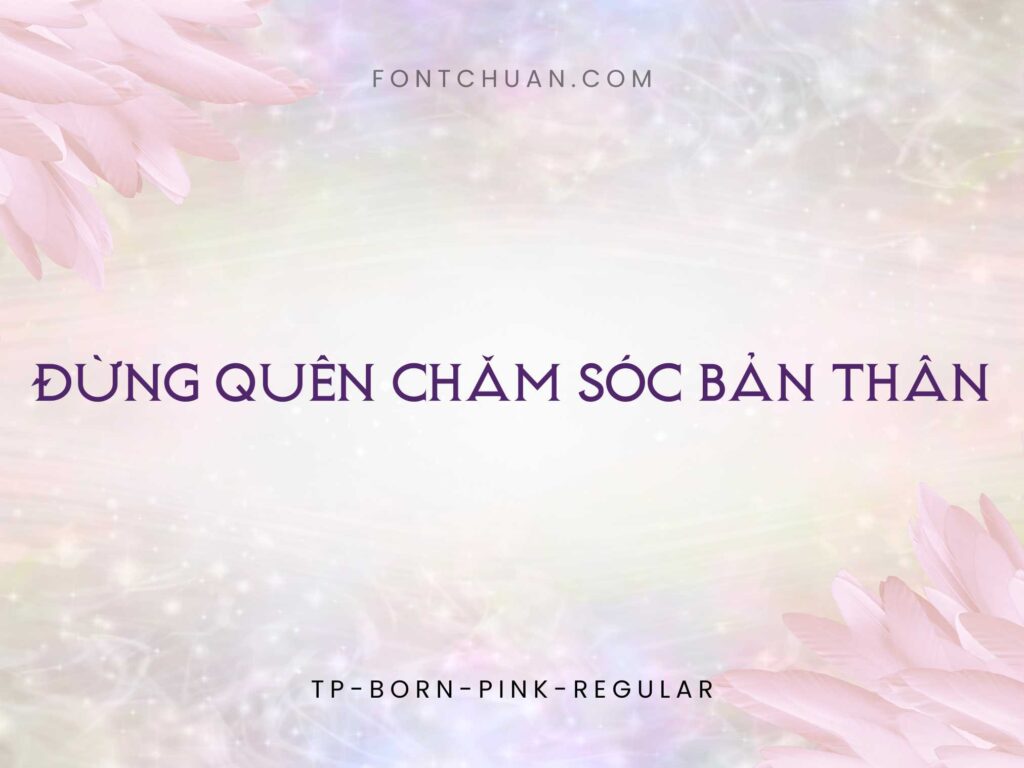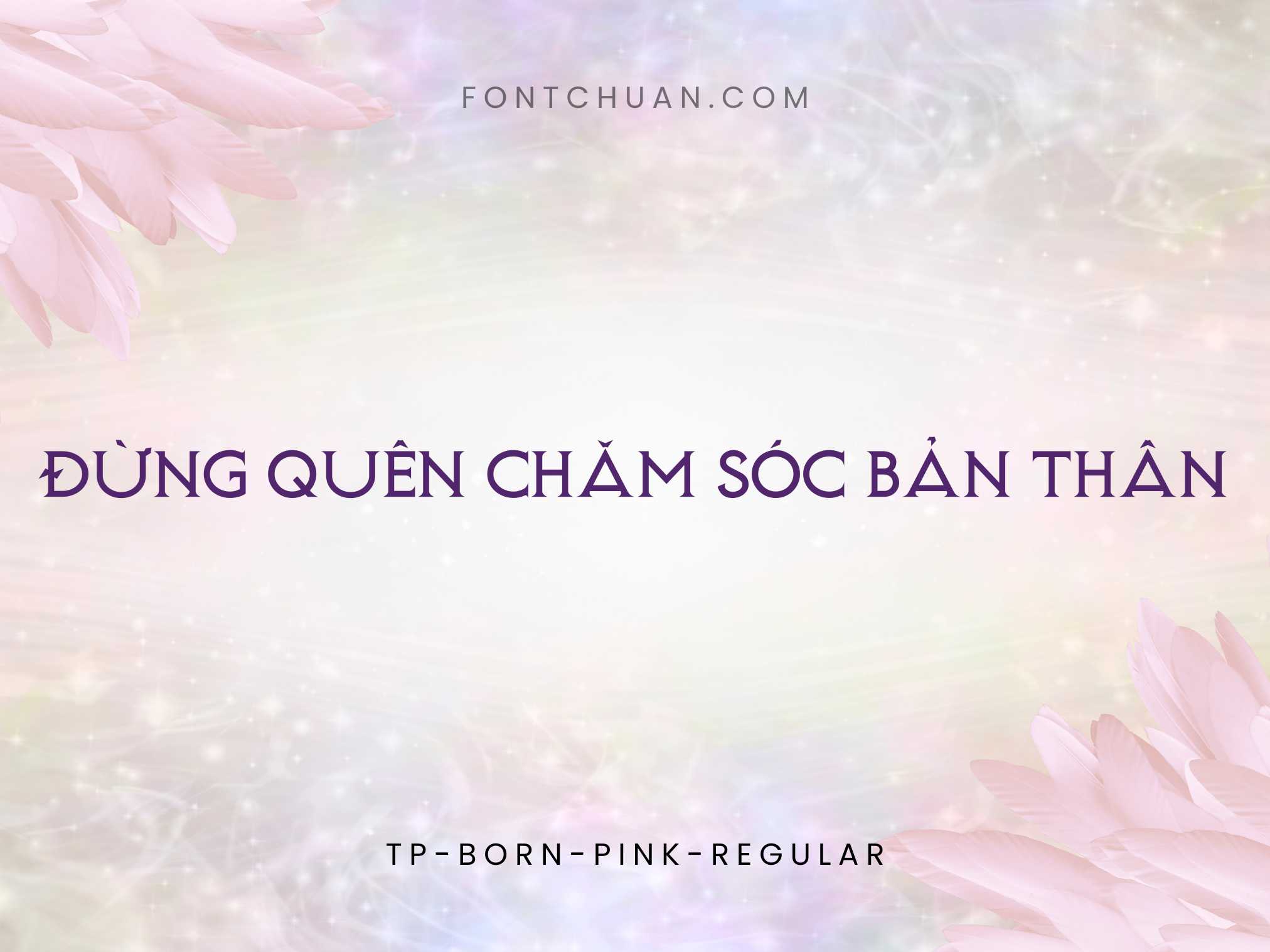
Font TP Born Pink Việt Hóa
Tác giả Font: Tuỳ Pucca Dựa Theo Font Exocet
Born Pink là một font chữ được phát triển dựa trên phông chữ Exocet và lấy cảm hứng từ dòng chữ trên poster concert BORN PINK của nhóm nhạc nữ BLACKPINK. Font này mang phong cách hiện đại và độc đáo, phù hợp cho các dự án thiết kế liên quan đến âm nhạc, giải trí và thời trang. Font đã được Việt hóa để hỗ trợ tiếng Việt bởi Tuỳn Pucca, đồng thời hỗ trợ nhiều ngôn ngữ khác, giúp mở rộng phạm vi sử dụng trên toàn cầu. Font này được sưu tầm và chia sẻ bởi thành viên của Font Chuẩn, đáp ứng nhu cầu của người dùng và ứng dụng thực tế vào các dự án thiết kế.
Đặc điểm thiết kế của Born Pink bao gồm các đường nét sắc sảo và hiện đại, tạo cảm giác mạnh mẽ và cá tính. Font này phù hợp cho các ứng dụng như tiêu đề, logo, poster và các dự án sáng tạo khác. Các ngành nghề phù hợp bao gồm thời trang, giải trí và truyền thông.